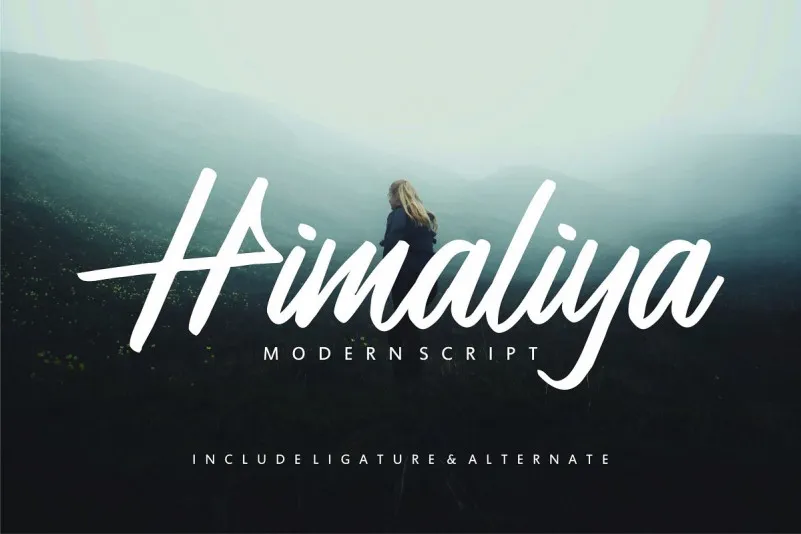
Himaliya Script Font – Download Grátis
Himaliya Script Font é uma opção perfeita para aqueles que buscam uma fonte criativa e elegante para seus projetos pessoais ou comerciais. Inspirada na arte do caligrafia, essa fonte apresenta um estilo único e casual, adicionando um toque delicado a qualquer projeto de design. Este conjunto de fontes se destaca como ideal para designs rurais e projetos de campo, proporcionando um ar natural ao seu trabalho. Introduzida pela designer Vunira, Himaliya Script Font é uma maravilha visual em cartões de convite, materiais de marca, cartões de visita, citações, painéis publicitários e muito mais. Suas linhas curvas suaves e sua personalidade são perfeitas para agregar um toque especial aos seus projetos. Experimente a Himaliya Script Font e descubra o encanto que ela pode trazer à sua próxima criação visual.